■■■ チャイニーズ・スタイル 欧文フォントあれこれ ■■■
〜エキゾチックでハイセンス!〜
中国語の文字は歴史があり、独特のスタイルを持っています。その美しい形態は、
ラテン系アルファベットとの組み合わせにおいて西洋のデザイナーを触発してきました。
今回は、中国語フォントそのものではなく、中国語風のフォントの特集です。
筆書きの印象を与える文字や、アジアの活気を伝える文字を集めてみました。どうぞご覧下さい!
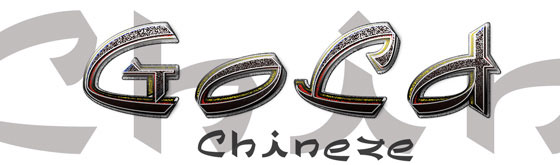
メニューや漫画、食料品のパッケージなどにどうぞ。
(Light、Medium、Boldの3ウェイトございます)
Linotype Chineze Light
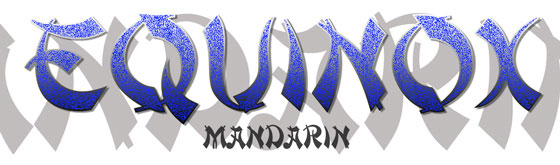
古代中国の高官の名前を冠した書体です。
メニューやアジア料理店の広告をはじめ、アジア製品の商取引に最適です。
Mandarin Regular
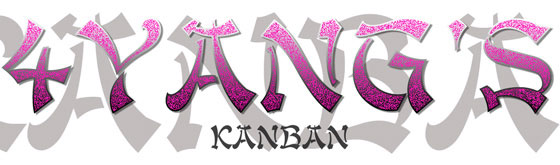
イギリスのデザイナー、エド・バグによる書体です。全て大文字で、東洋的なスタイルです。
Kanbanというのは、日本の店先に屋号などを掲げる板(もちろん、「看板」のこと)から名付けられました。
東洋的な雰囲気を出したい時にはどこでもお使いいただけます。
Kanban Plain
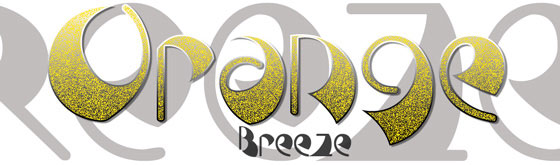
これはアジアから直接的に影響を受けた書体ではありませんが、
このコレクションとうまく調和するのでご紹介します。
太いところと細いところの対比が強調されています。
Breeze Left
|
| Breeze Right
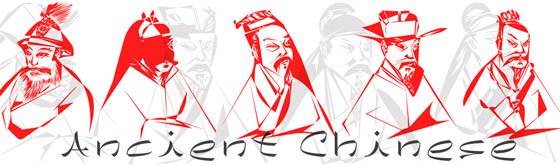
これはピーター・キンファン・ローがデザインし、
1997年に賞を受賞しているフォントです。
古代中国の人物を施したものです。
ディテールを生かすには、少し大きなサイズでの利用がお薦めです。
Linotype Ancient Chinese Regular
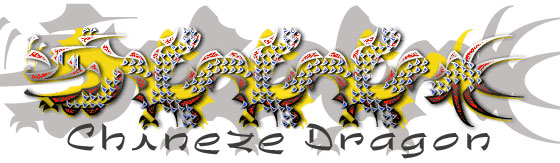
これは3つの部分から成り立ちどのような長さ・高さの中国龍を表現できます。
真っ直ぐなものも、曲がったものもお好きなように創り出すことができます。
Chineze Dragon Std 1
|
| Chineze Dragon Std 2
|
| Chineze Dragon Std 3
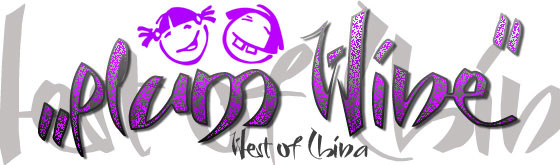
中国の伝統的なカリグラフィーと、現代的なグラフィティの中間に位置する書体です。
あなたのデザインに活気といきいきとした表情を与えてくれます。
West of China Regular
親しみやすい感情が表現された笑顔を集めてみました。
招待状や学校での書類、そしてファミリーにもぴったりです。お楽しみください!
Linotype Smileface Regular